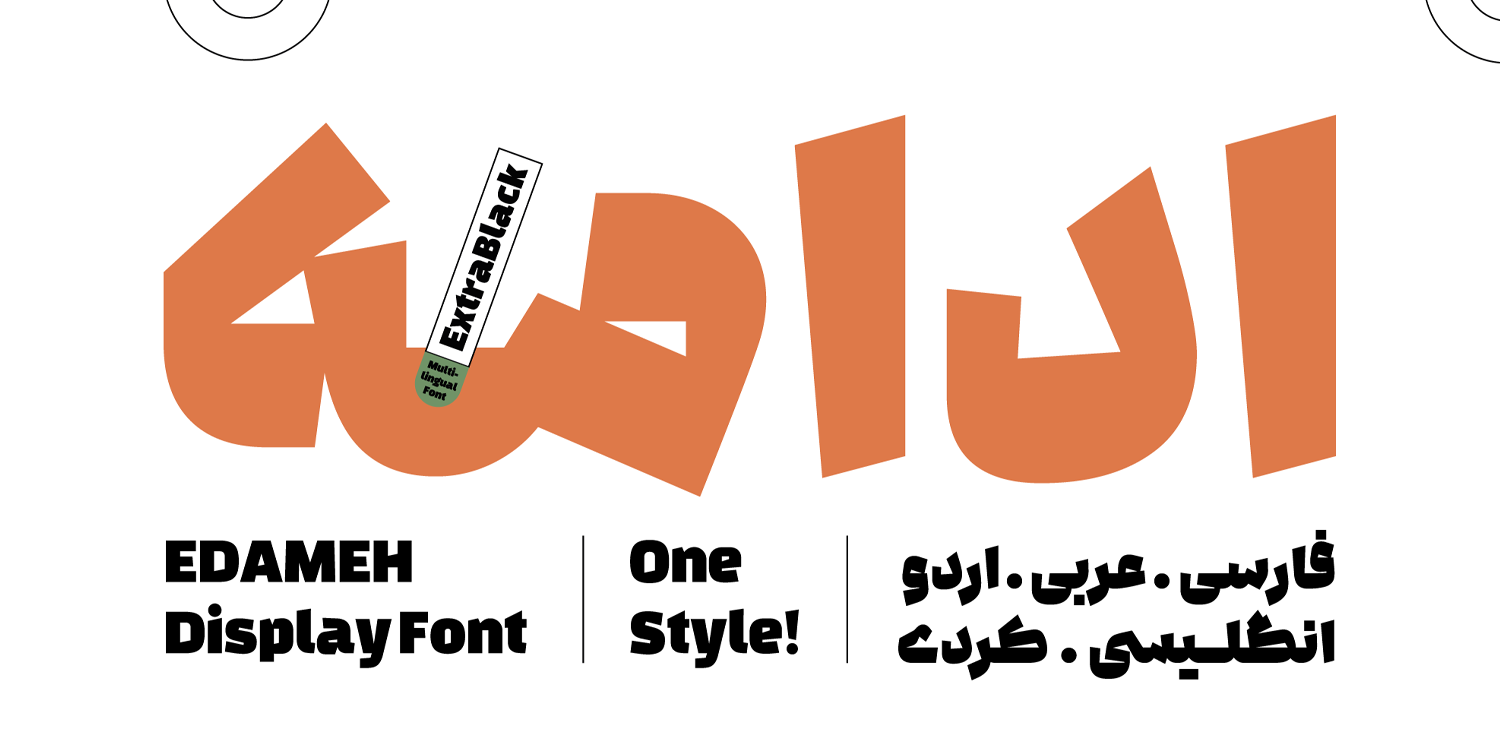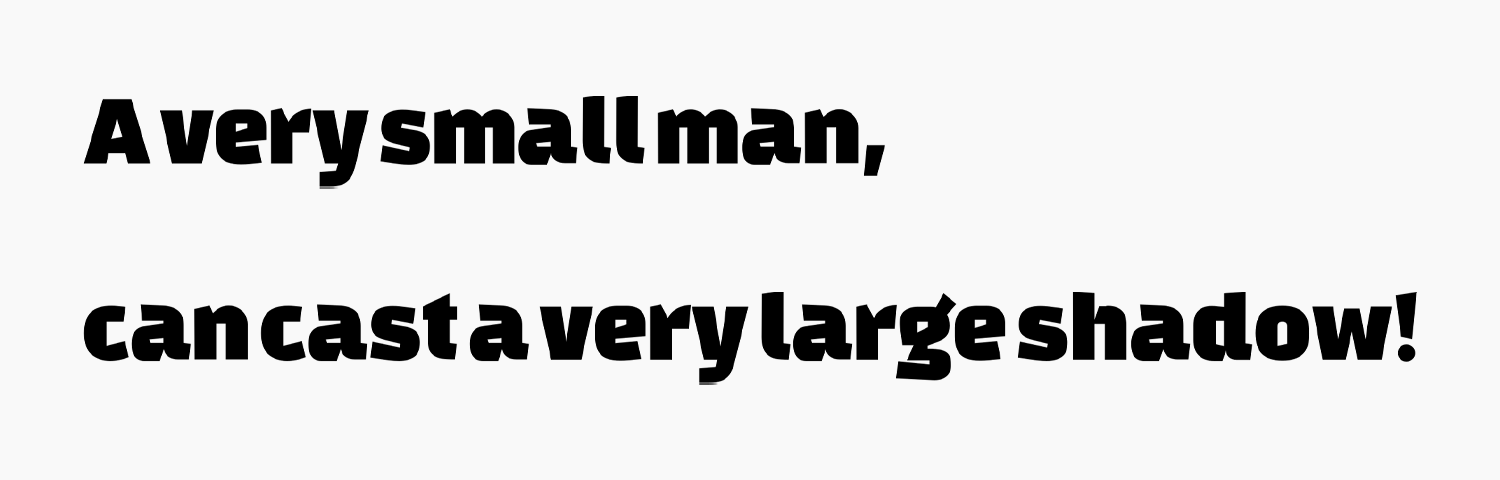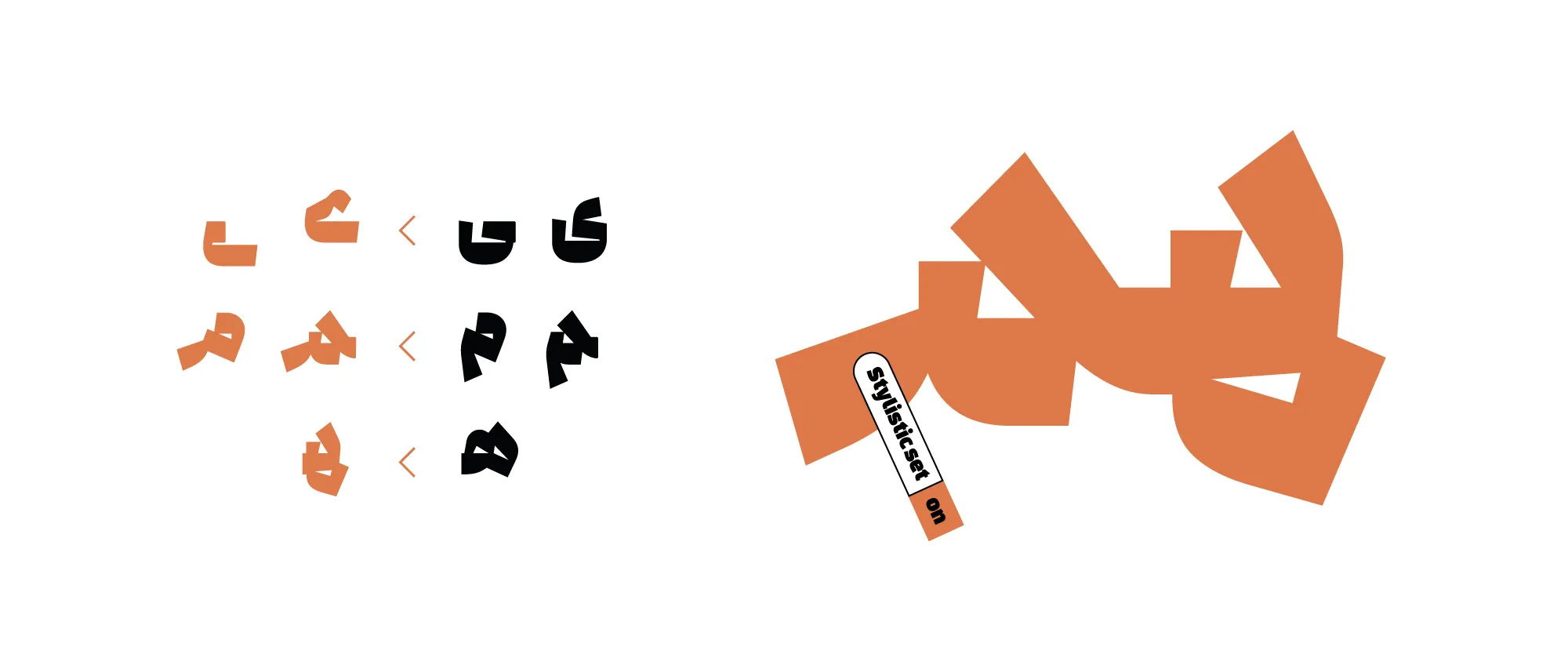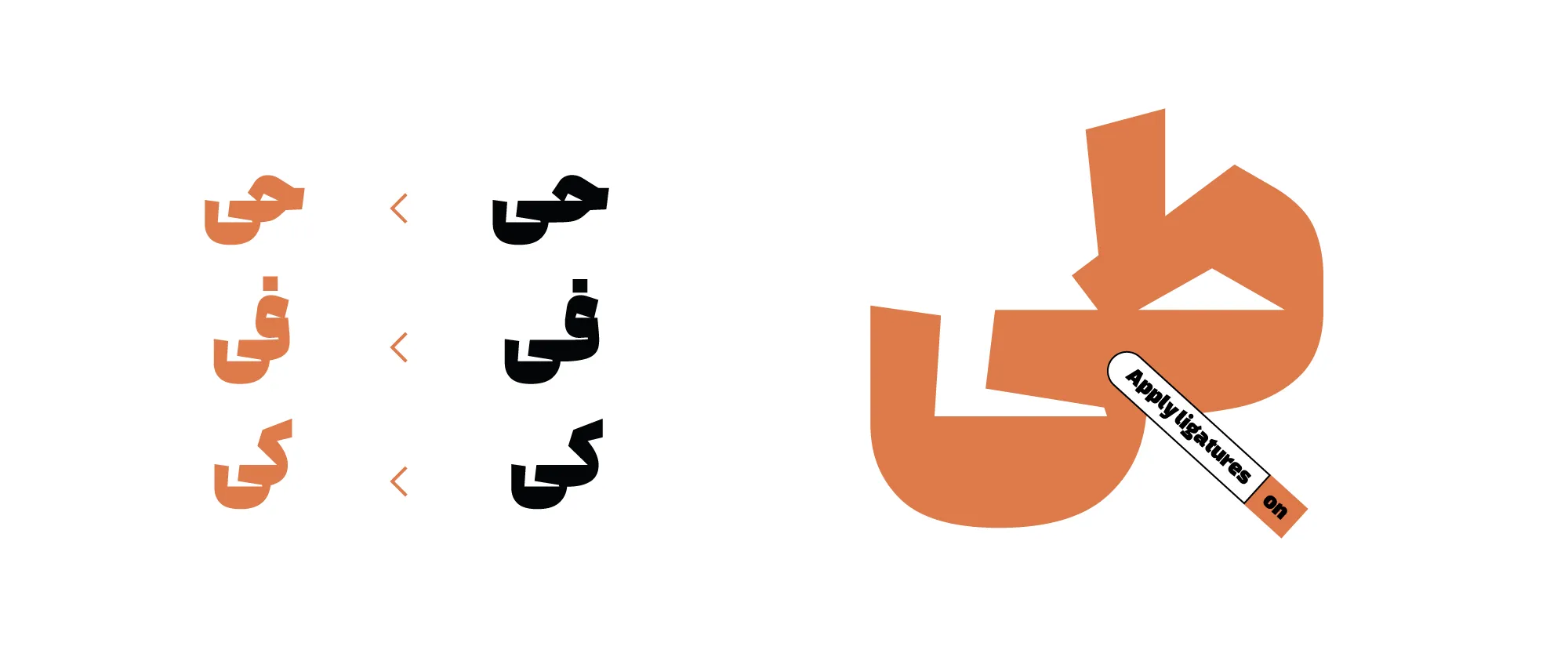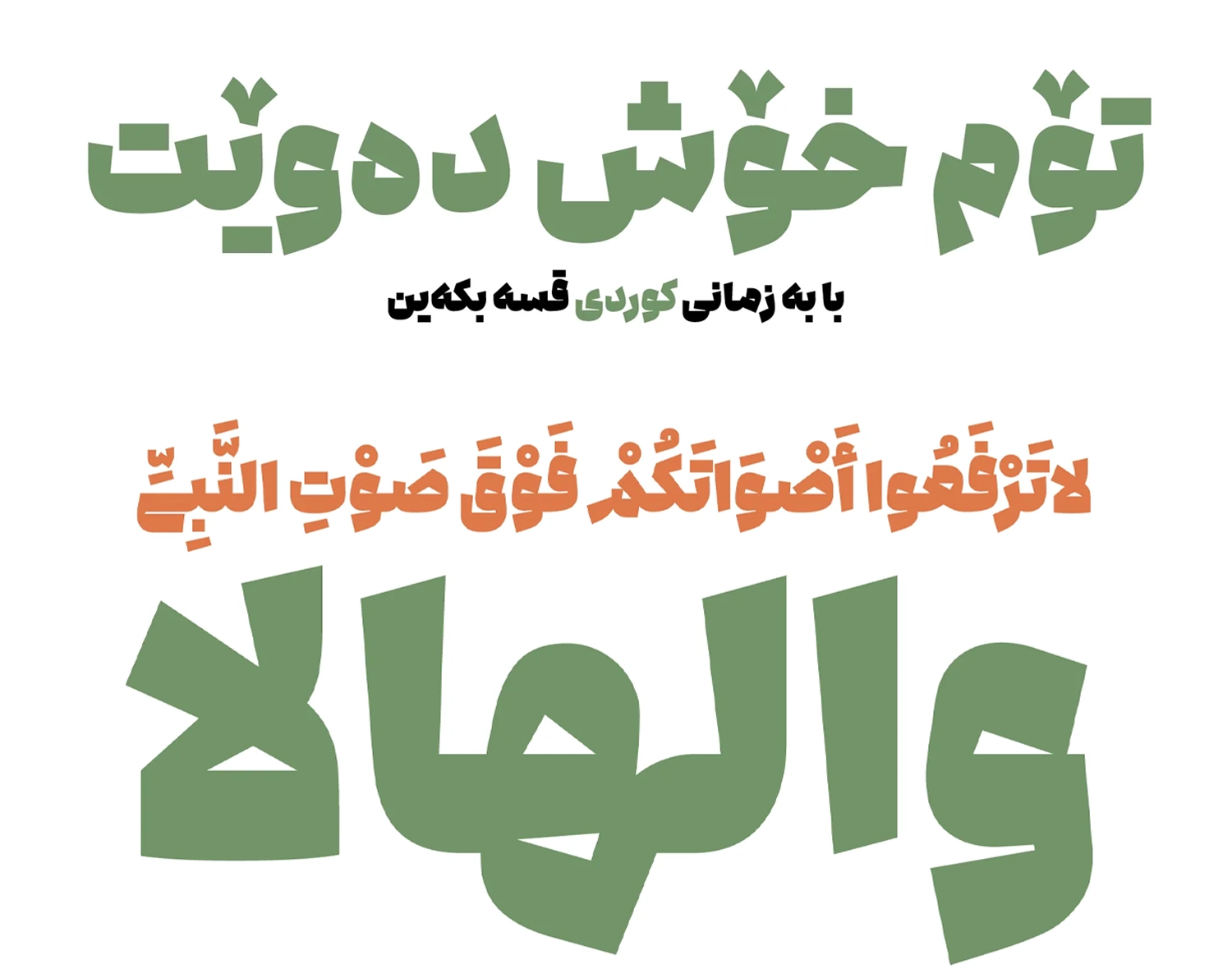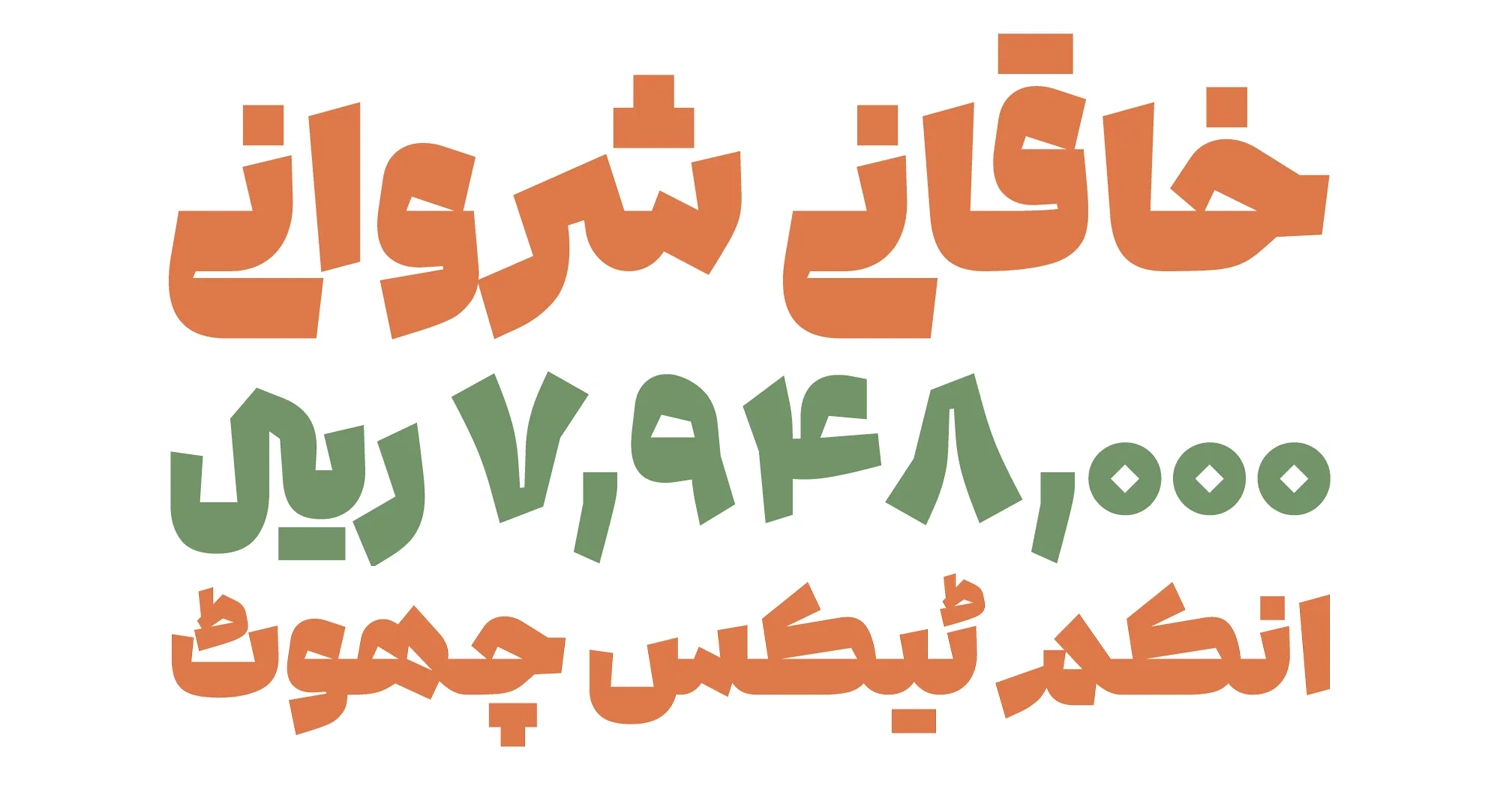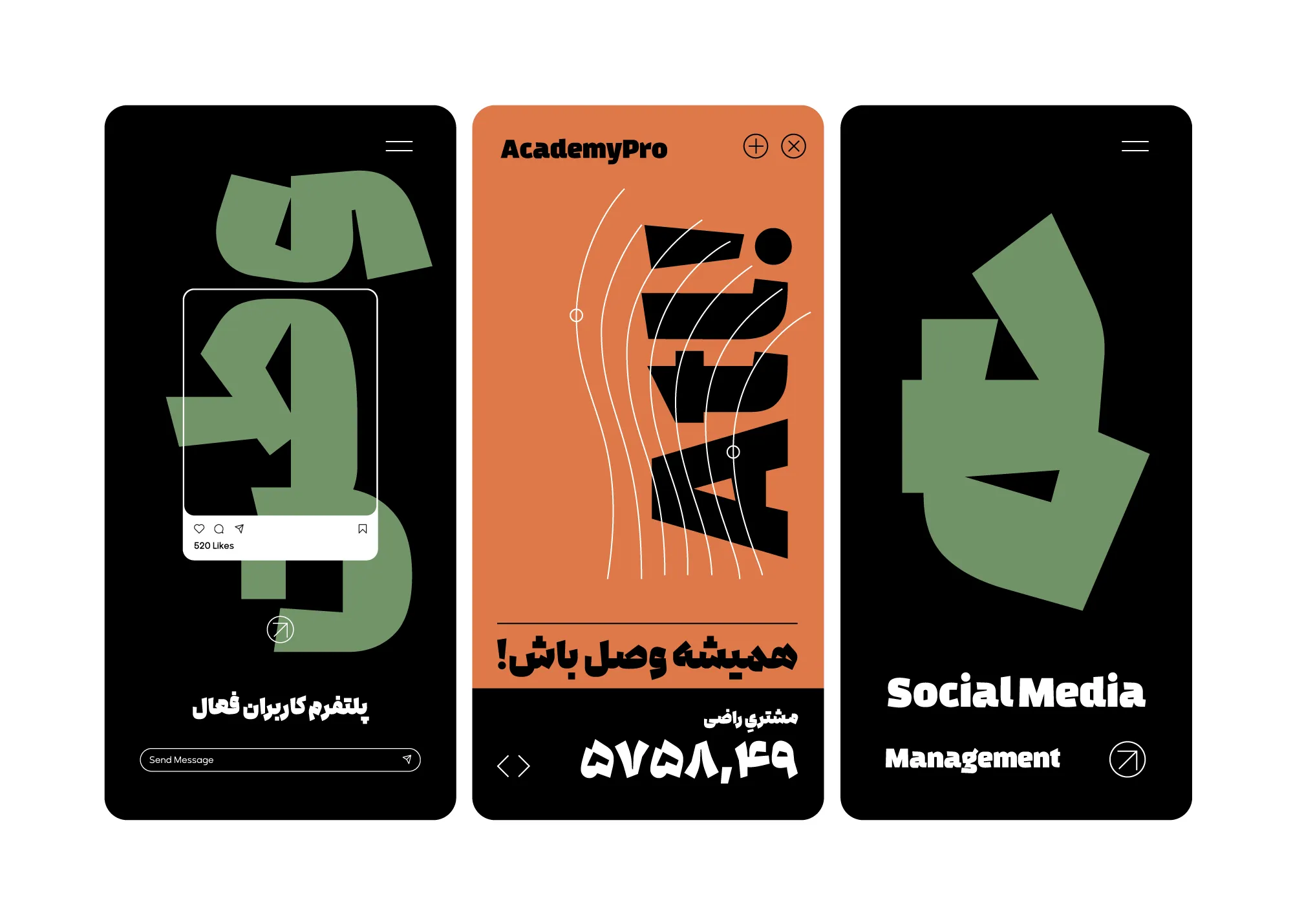
فونت ادامه (Edameh)
| نام | ادامه |
| نام نمایشی | edameh |
| طراح | سید ناصر خادم |
فونت ادامه (به انگلیسی: Edameh) یکی دیگر از جدیدترین فونتهای هندسی معرفی شده فارسی است که دارای وزن فوق سنگین بوده و برای استفادههای تبلیغاتی و عناوین مناسب است. این قلم با توجه به ضخامت و سبک طراحی که دارد، توجه بیننده را به خود جذب خواهد کرد.
طراح این فونت سید ناصر خادم است، که این قلم را با مطالعه بر روی ساختار هندسه خوشنویسی ایرانی در کلاس استاد دامون خانجانزاده ایجاد نموده است. ساختار این قلم در نتیجه تغییر اتودهایی در هندسه خوشنویسی ایرانی ایجاد شده که فرم سنگینی نیز به آن داده شده است و استفاده از آن را در عناوین و کلمات تککلمهای مناسب ساخته است.
در ادامه این نوشته از سایت فونتچی به نقد و بررسی فونت ادامه خواهیم پرداخت؛ قلمی که با وزن فوق سنگین خود برای استفاده در تیترها، عناوین، محتوای تبلیغات و همچنین استفاده در تامنیلهای شبکههای اجتماعی میتواند مناسب باشد. خصوصا در اندازههای بزرگ که ساختار نمایشیتری دارد.
فونت ادامه با اینکه صرفا یکوزن دارد، اما از شخصیتی چندگانه برخوردار است. گاهی در فرم یک حرف، تیزی و خشکی را در کنار منحنی میبینید و گاهی نیز از حروف و ترکیباتی در یک کلمه استفاده شده که فونت را کاملا رسمی و خشک نشان میدهد.
چشمی حروف دارای فضای منفی مثلثی هستند در حالی که فرم کلی حروف مانند مفتول فولادی خمیده دیده میشود. تاکید بر فرمهای چشمگیر حروف در عین توجه به ظرافتهای طراحی، طراحان و مدیران استارتاپها و بهویژه کسب و کارهای آنلاین را به استفاده از این فونت در تیتر مطالب خود فرا میخواند.
سبک طراحی و وزن فونت ادامه
فونت ادامه بر اساس خوشنویسی ایرانی طراحی شده که ساختاری مدرن و امروزی در قالب حروف هندسی به آن داده شده است. این فونت با اینکه صرفا از یک وزن ExtraLight پشتیبانی میکند و برای استفاده در عناوین و تیترها درنظر گرفته شده، اما به لطف قابلیت پشتیبانی از ترکیبات آلترنیتیو و حروف جایگزین امکان تایپ کلمات به شکلهای متنوعی را در اختیار قرار میدهد.
در این فونت دندانهها، زوایا، گردی حروف و شروع و پایان آنها دارای یک طراحی جدید هستند که در فونتهای دیگر چنین طراحی دیده نشده است. شاید صرفا بتوان گفت در فونت گفته که چند ماه پیش منتظر شد، به شکل بسیار محدودی، اما با این تفاوت که ساختاری گردتر دارد چنین ساختاری را دیدهایم.
پشتیبانی از ۵ زبان متنوع و کامل
فونت ادامه یک فونت همهفن حریف و چند زبانه است که بر اساس ساختار یونیکد بین المللی طراحی شده است. در این فونت تمامی حروف، کاراکترها و گلیفهای هر زبان با استاندارد بین المللی طراحی شده و اگر در یک زبان خاورمیانهای نظیر اردو و عربی تفاوت جزئی یا حتی فاحشی در شکل و ظاهر حروف و ترکیبات وجود داشته باشد، چه در حالت تکحرف و چه در ترکیبات جایگزین رعایت شده است.
پشتیبانی این فونت علاوه بر زبان فارسی شامل سایر زبانهای مبتنی بر این خط همچون اردو، کردی و عربی است. هی یک از این زبانها دارای شکل اختصاصی حروف خود هستند. برای مثال حروف «ك، ي، ة، ؤ، ئ» در زبان عربی که متفاوت از فارسی هستند رعایت شده و دارای نقاط و همزه بر زیر و بالی حروف هستند.
یا در زبان اردو حروفی مثل «ﮧ، ﮩ، ے» نهتنها دارای گلیف اختصاصی خود هستند، بلکه از برخی آنها برای سایر زبانهای فارسی و عربی بهمنظور استفاده برای حروف جایگزین در نظر گرفته شده است.
این فونت از نظر اعراب گذاری عربی و همچنین استفاده از گلیفهای تزئینی و طرهها در زبان های کردی و اردو کامل بوده و شامل برخی گلیفهای خاص نیز میباشد که در ادامه بیشتر آنها را بررسی میکنیم.
از نظر زبانهای لاتین این فونت از حروف انگلیسی نیز با همان سبکی که برای حروف فارسی در نظر گرفته شده است پشتیبانی میکند. حروف در ابتدا دارای ضخامت کمتر بوده و در پایان ضخامت آنها بیشتر میشود. همچنین با تغییر گردی و زاویه خطوط نیز شکستگیهایی به شکل تیز و گاها نرم برای بخشهای داخلی و بیرونی درنظر گرفته شده است.
دارای ترکیبات و حروف جایگزین
مهمترین ویژگی یک فونت تبلیغاتی پشتیبانی از حروف جایگزین است. حال میتواند این حروف جایگزین با استفاده از پشتیبانی وریبل همراه باشد که بتوان در وبفونت نیز استفاده کرد یا اینکه از طریق تنظیمات Open Type نرمافزارهای گرافیکی قابل استفاده باشد.
وجود ترکیبات جایگزین کمک میکند تا برای استفادههای تبلیغاتی برخی حروف دارای شکل متفاوتی نسبت به سایر کلمات باشند که همین مسئله میتواند روی جلب توجه بیشتر نگاه مخاطب تاثیرگذار باشد. حتی اگه مخاطب نگاه کاملا مستقیمی به تکتک حروف و کلمات نداشته باشد.
حروف جایگزین این فونت شامل ترکیبات متعددی است که میتوانید در فایل راهنمای بسته دانلود فونت ادامه آنها را مطالعه و طریقه استفاده را نیز بررسی کنید. اما برای نمونه چندتا از آنها را بررسی میکنیم.
برای تایپ حروف «ک» و «گ» کشیده در فونت ادامه میتوانید حالت Swash را در تنظیمات Open Type فعال کنید تا مشابه با نمونههای بالا بسته به اینکه در ابتدا، میانه یا انتهای کلمات باشند تایپ شوند.
دیگر حروف جایگزین فونت ادامه شامل «ی»، «م»، «هـ» است که میتوانید با فعال کردن Stylistic Set در تنظیمات Open Type از آنها مانند تصویر بالا استفاده کنید.
با فعال کردن حالت apply Ligaturs در تنظیمات Open Type نیز میتوانید از حالت ترکیبات کشیدگیهای منتهی در حروف «ی» استفاده کنید.